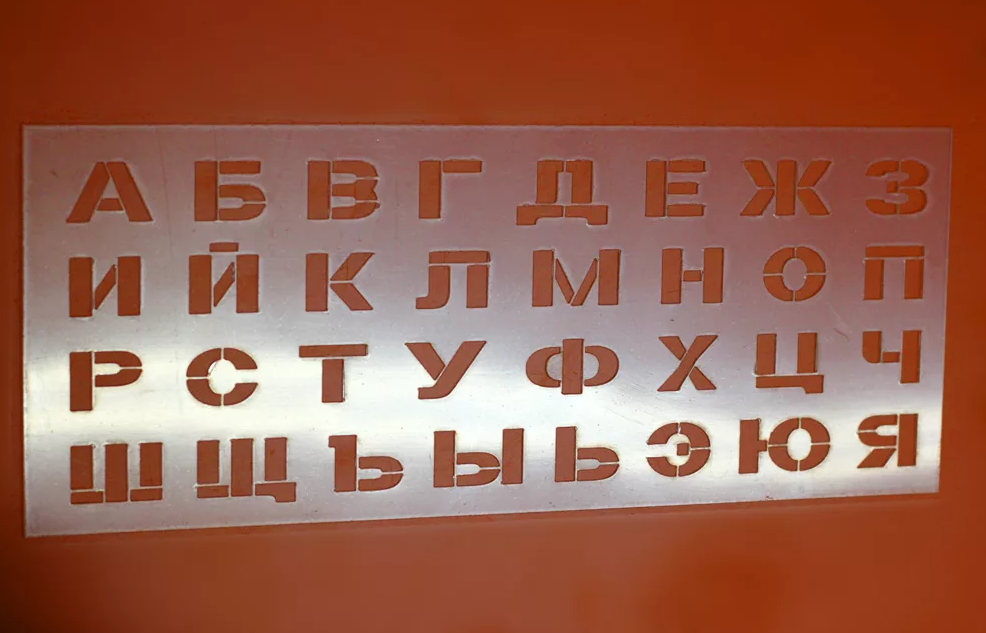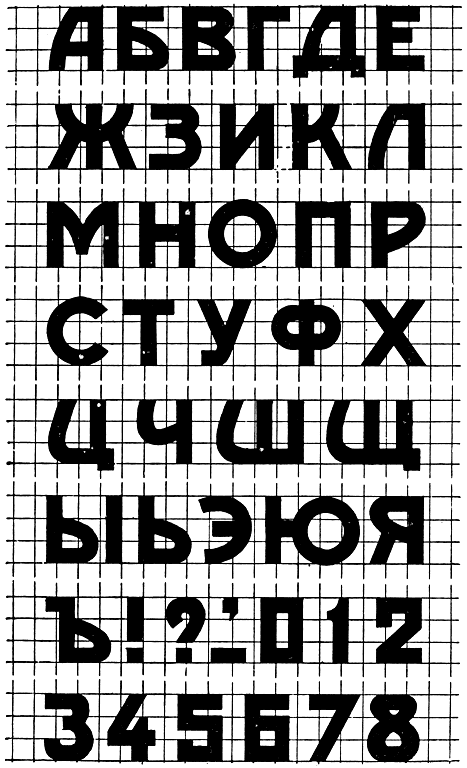
Трафаретные шрифты для надписей маркировочных знаков и эмблем на автотранспорте
Считаем целесообразным представить несколько наиболее популярных и близких к аутентичным трафаретных шрифтов, которые могут быть использованы в качестве надписей к эмблемам АТП, маркировке грузов и т.
д. при изготовлении масштабных моделей. При выборе варианта покраски модели автобуса рекомендуем следовать требованиям из ГОСТ 24348-80, который регламентирует порядок нанесения цветографических схем на городские автобусы и автобусы дальнего следования. Также желательно ознакомиться с рекомендациями по нанесению эмблем и номеров, где указаны их точные размеры, место расположения и требования к применяемым цветам согласно картотеки ЛКМ.
Образец трафаретного шрифта Sunline Trafaret.
Образец трафаретного шрифта Aero Matics Stencil.
Образец трафаретного шрифта Danger.
Образец трафаретного шрифта Depot Trapharet 2D.
Некоторые примеры использования трафаретных шрифтов представлены в нашей коллекции реальных прототипов эмблем АТП, предприятий и ведомств времен СССР, наносившихся на транспортные средства различного назначения.
Трафарет «Испытания» на маршрутном указателе ЛАЗ-699А «Карпаты» Опытный II.
Трафарет отрисован с маршрутного указателя оригинальной фотографии автобуса ЛАЗ-699А «Карпаты» Опытный II.
Файл трафарета с прозрачным фоном лежит здесь. Любителям скрупулёзного создания моделей придется закрасить перемычки в букве «ы» (в экспериментальном цеху ЛАЗа, по видимому, с этой буквой были проблемы).
Шрифт из стандарта ГОСТ 14192-96
Ещё один популярный, но зачастую неверно используемый среди моделистов шрифт — из документа ГОСТ 14192-96 «Маркировка грузов», устанавливающий общие правила маркировки грузов. Документ был введен в действие 01.01.1998 взамен ГОСТ 14192-77 (до этого — ГОСТ 14192-71) и предлагал три типа шрифтов (хотя и допускал использование других шрифтов в случае механизированного нанесения), последний из которых (тип 3) представлен ниже. Отличается он одинаковой шириной букв и цифр, а также закругленными окончаниями элементов букв.
Шрифты тип 1 и тип 2 из ГОСТ 14192-96.
Шрифт тип 3 из ГОСТ 14192-96.
Образец трафаретного шрифта ГОСТ 14192-96 (тип 3).
Шрифт из стандарта РФ ГОСТ Р 50574-2002
Ниже представлен растровый образец шрифта надписей и цифр из Государственного стандарта РФ ГОСТ Р 50574-2002 «Автомобили, автобусы и мотоциклы оперативных служб.
Цветографические схемы, опознавательные знаки, надписи, специальные световые и звуковые сигналы. Общие требования». Стандарт вступил в силу 15 декабря 2002 года и в настоящее время является действующим на территории РФ. Шрифт находится в обязательном «Приложении Б» данного документа и содержит только заглавные буквы (прописные не используются).
ГОСТ Р 50574-2002 достаточно большой по объему информации, тем не менее, рекомендуется для ознакомления коллекционерам и создателям масштабных моделей, поскольку содержит примеры цветографических схем и расположения надписей на транспорте всех видов оперативных служб.
Кстати, документ ссылается на всё ещё действующий ГОСТ 19715-74 (введен в действие 30.06.1975), которым регламентируются форма и размеры эмблемы Красного Креста. Эта маркировка наносится на материальные средства медицинской службы, в том числе и на санитарные автомобили и специальные средства транспорта. Одним из таких ранних спецсредств был санитарный ЛАЗ-695Б — автобус для перевозки раненых, созданный львовянами в 1959 году в качестве опытного образца.